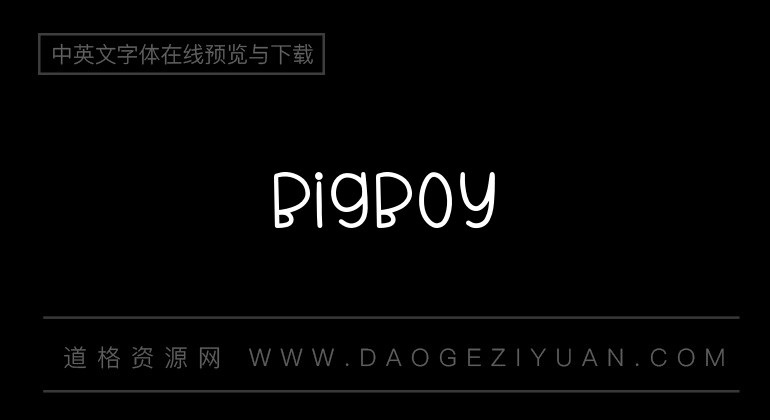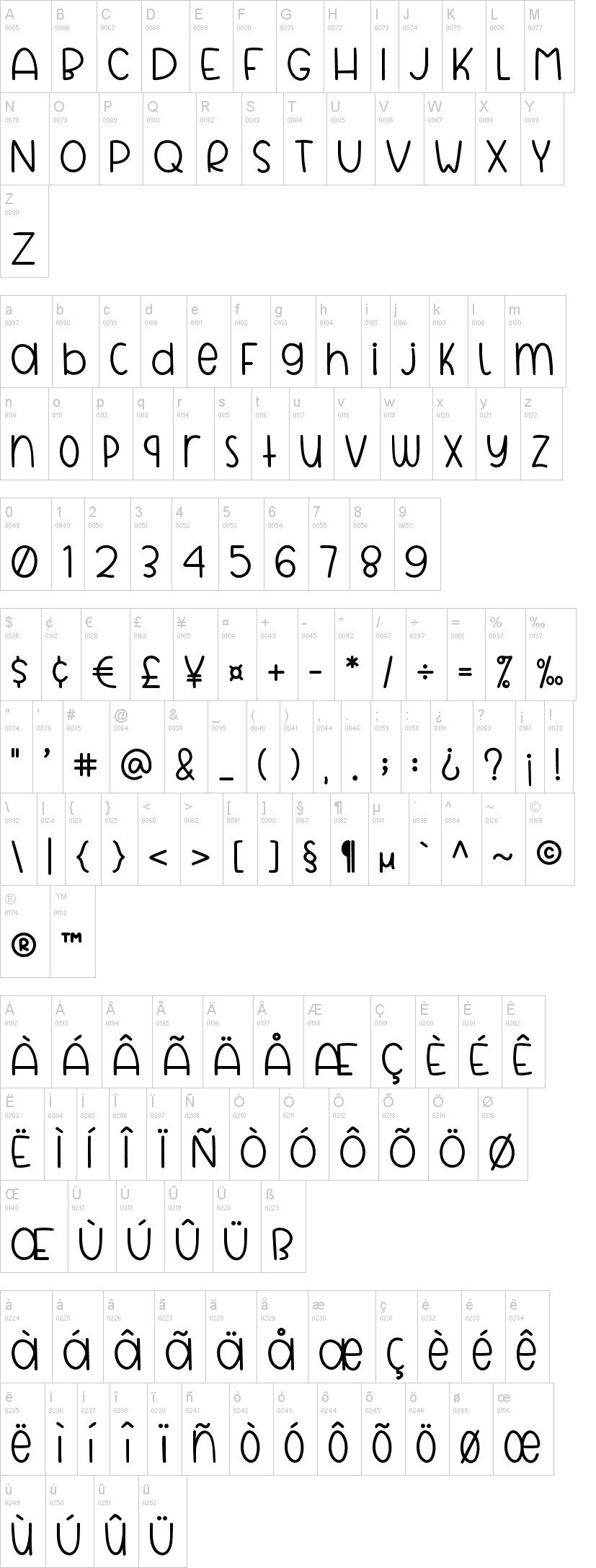
? BigBoy字体是一款拥有极具个性的字体,它的外形让人想起了英文字母的拼写,让人看起来更加有趣。它的字体样式更加大胆,更能够表达出现代设计语言的特点。它的独特外观和个性,使它成为一款受欢迎的字体,在排版、图形设计和插图等领域都有着广泛的应用。内容介绍
BigBoy是一款非常不错的手写艺术字体,具有很好的视觉感,适合于文化类的宣传设计、商业类品牌的广告和产品包装设计以及个性化文字排版等较多场景。